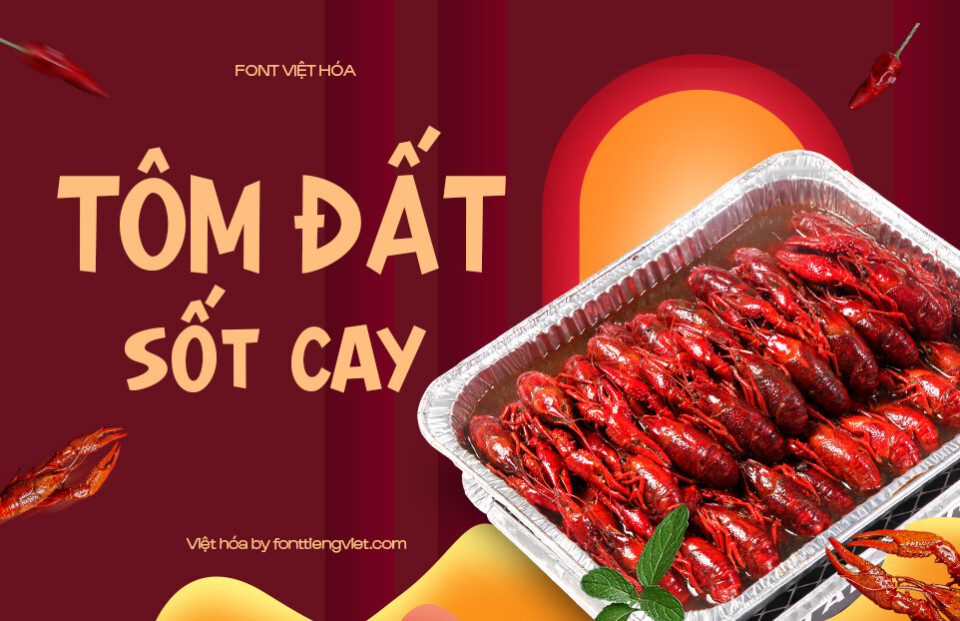
Giới thiệu bộ Font Việt hóa 1FTV VIP Komika chuyên nghiệp
Trong thế giới đồ họa hiện đại, việc lựa chọn một Font Chữ phù hợp đóng vai trò quyết định đến linh hồn của tác phẩm. Font Việt hóa 1FTV VIP Komika là một trong những bộ phông chữ phong cách comic phổ biến nhất hiện nay. Được tinh chỉnh kỹ lưỡng về dấu tiếng Việt, bộ font này mang đến sự mượt mà và đồng nhất cho các dự án sáng tạo. Với đường nét đậm, chắc khỏe nhưng không kém phần vui nhộn, đây là lựa chọn số một cho các bạn học sinh và giáo viên khi thực hiện các bài thuyết trình sinh động hoặc trang trí báo tường điện tử.
Ưu điểm nổi bật của phông chữ Komika
Đặc điểm lớn nhất của Font Việt hóa 1FTV VIP Komika chính là tính ứng dụng cao trong nhiều hoàn cảnh khác nhau. Kiểu chữ này giúp nội dung trở nên dễ đọc, thu hút ánh nhìn ngay từ giây đầu tiên. Không chỉ dành riêng cho truyện tranh, bạn có thể sử dụng nó để làm tiêu đề video, thiết kế áo lớp hay các bảng biểu trong nhà trường. Sự phá cách trong từng nét chữ giúp truyền tải thông điệp một cách năng động và tràn đầy năng lượng tích cực đến người xem.
Cách ứng dụng Font Việt hóa 1FTV VIP Komika vào học tập
Để tận dụng tối đa vẻ đẹp của bộ font này, người dùng nên kết hợp với các gam màu rực rỡ như vàng, đỏ hoặc xanh dương. Việc cài đặt cũng vô cùng đơn giản, tương thích hoàn toàn với các phần mềm văn phòng cơ bản như Word, PowerPoint hay các công cụ thiết kế chuyên sâu. Font Việt hóa 1FTV VIP Komika sẽ biến những trang giáo án khô khan trở nên hấp dẫn hơn, kích thích sự sáng tạo của học sinh trong mỗi tiết học thú vị.